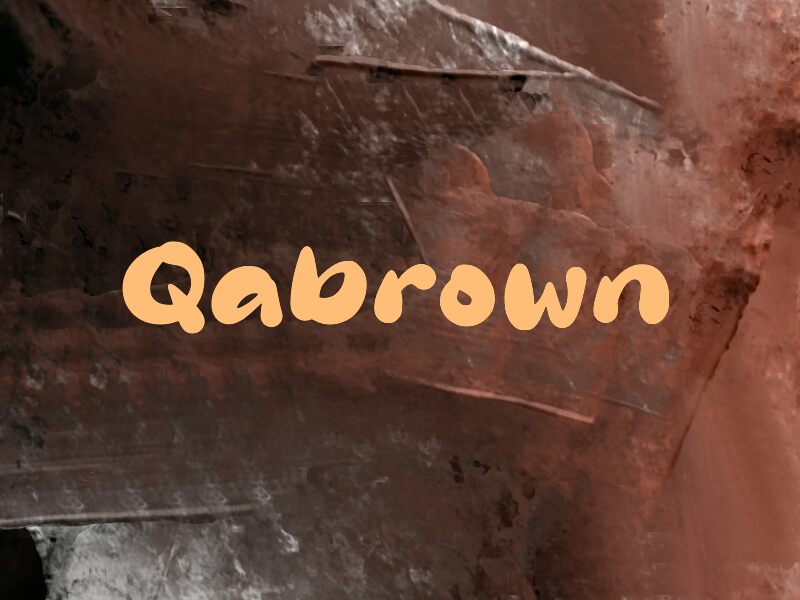
Qabrown
Qabrown, da Wep, é uma fonte display estilo cartoon composta por formas arredondadas e volumosas que parecem ter sido moldadas, não apenas desenhadas. Essa silhueta «fofinha» confere às letras um movimento suave e divertido, enquanto as curvas irregulares e as aberturas fechadas a distinguem dos estilos de fonte em bolha comuns.
Funciona perfeitamente em títulos curtos, embalagens infantis, convites, autocolantes e gráficos criativos para redes sociais. A sua massa sólida e ritmo ligeiramente assimétrico dão aos títulos, promoções de apps ou merchandising a presença necessária para quem procura uma voz amigável, direta e levemente descontraída.